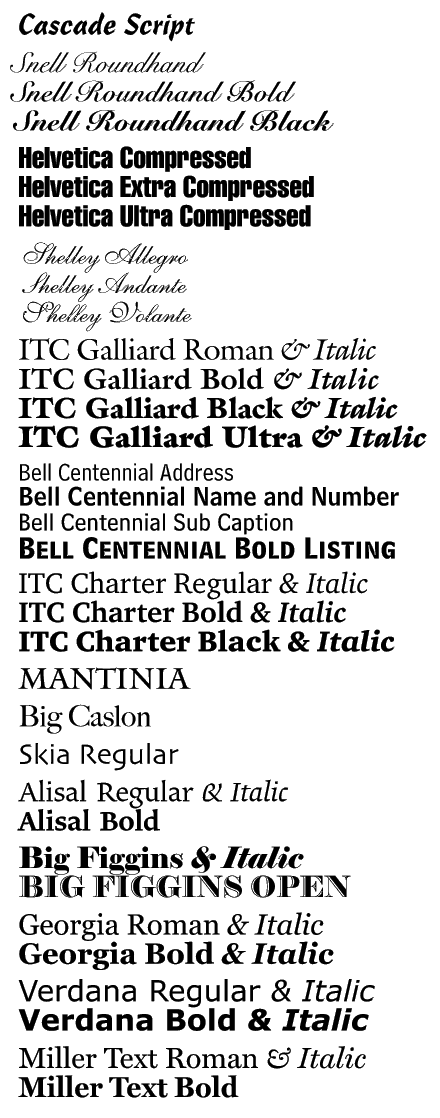
Matthew Carter (1937 -
Este designer de tipos britânico começou a trabalhar com tipos metálicos nos anos 50, para depois acompanhar todas as revoluções em tecnologia - o que o fez mais apto a tirar todas as vantagens de cada uma delas. Carter é uma «velha raposa» da profissão dos typeface designers.
M Carter
Nascido na Bretanha, estabelecido em Boston, este tipógrafo já trabalhou com tudo, dos tipos móveis de metal até às fontes digitais de computador. Foi considerado pela revista Print "talvez o designer de tipos em actividade mais completo da América".
Matthew Carter é um gentleman typeface designer britânico da velha guarda, activo na Europa e nos EUA, com mais de 40 anos de experiência em tecnologias tipográficas – desde a gravação de punções até às fontes digitais de hoje.
Depois de ter trabalhado largos anos para a Linotype, Matthew Carter, em parceria com Mike Parker, Cherie Cone e Rob Friedman, fundou a Bitstream, em 1981. Nesta fundição digital (a primeiríssima do género!) trabalhou dez anos; hoje dirige a Carter & Cone Type Inc., sedeada em Cambridge, Mass. (carterandcone.com).
Carter & Cone produziu tipos para empresas – ou melhor: para grandes impérios dos media e da informática – como a Apple, a Microsoft, a Time, a Newsweek, a Wired, a U.S. News & World Report, a Sports Illustrated, o Washington Post e outros.
Entre as fontes desenhadas por Carter contamos a Galliard BT (1982), a Snell Roundhand, as três Shelley Scripts (1972), a Helvetica Compressed, a Olympian, a Bell Centennial (para listas de telefone), a ITC Charter – além de fontes gregas, hebraicas, círilicas e devanagari. Já na Carter & Cone, Carter desenhou a soberba Mantinia, a Sophia, a Elephant, a Big Caslon, a Alisal e a Miller. P
ara a Microsoft, desenhou a Verdana e Georgia, fontes criadas para oferecerem a melhor legibilidade possível em monitores com baixa resolução.
Carter foi distinguido com o título Royal Designer for Industry, é membro da AGI, chairman do Type Designers’ Committee da ATypI e Senior Critic da Yale’s Graphic Design Faculty (para cuja universidade desenhou a fonte Yale).
Recebeu o F.W. Goudy Award pela sua outstanding contribution to the printing industry, o Middleton Award do American Center for Design, o Chrysler Award for Innovation in Design, a AIGA Medal e ainda a Type Directors Club Medal.
A era digital
Em 1981, Carter foi co-fundador da Bitstream, uma pioneira na fundição digital de tipos.
Actualmente é director da Carter & Cone Inc., empresa onde tem desenhado fontes como a Sophia, Big Caslon e Miller, para clientes como, Apple, Microsoft, o Centro de Artes Walker e o Washington Post.
Os trabalhos de Carter incluem a Vincent, uma fonte de texto e tela para a Newsweek; uma fonte de texto de jornal para o The Guardian, de Londres; e um trabalho contínuo com a Microsoft com fontes a serem usadas nas telas dos computadores.
A elegantíssima Snell Roundhand foi desenhada em 1965/66 por Matthew Carter para sistemas de fotocomposição. Baseia-se na letra do mestre calígrafo britânico Charles Snell, que viveu no século XVIII. A fonte digitalizada é oferecida em três pesos: Snell Script, Bold Script e Black Script.
A fonte Yale foi encomendada pela Universidade do mesmo nome, e a sua utilização vai do uso administrativo à sinalização do campus da instituição. O projecto teve como base histórica de desenvolvimento os tipos feitos para Aldus Manutius, entre 1495 e 96, para a obra De Aetna.
Algumas das mais usadas fontes de Carter.
Carter recebeu a Medalha AIGA, a medalha do Clube dos Directores de Tipos, o Prémio Frederic W. Goudy e o Prémio Middleton do Centro Americano.